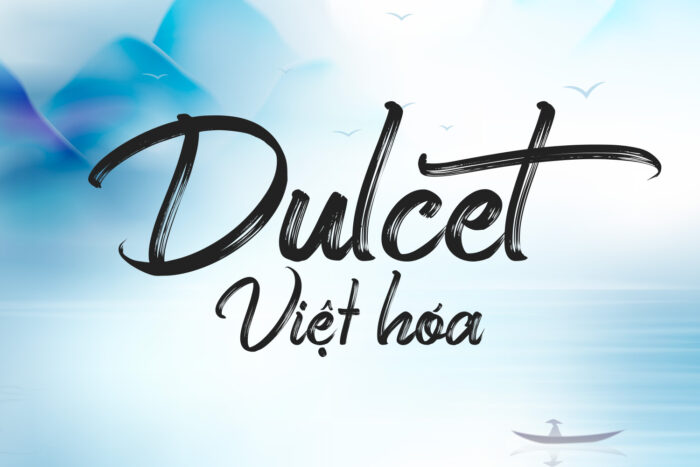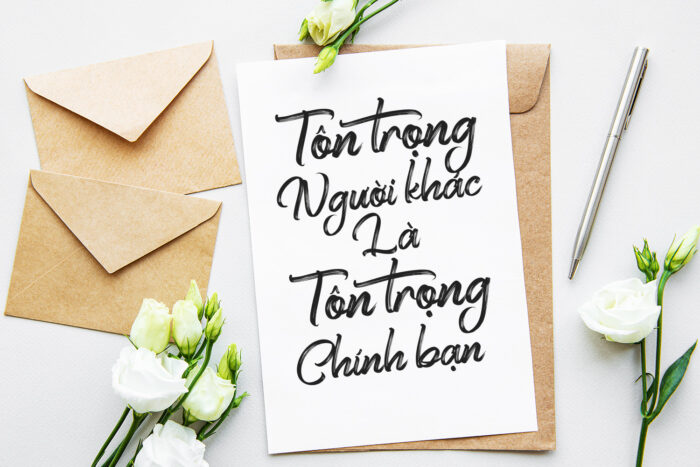
DVN Dulcet Script Việt hóa – Font chữ thư pháp tuyệt đẹp
“Dulcet Script” là một font chữ viết tay mang phong cách thư pháp, thể hiện sự uyển chuyển và mềm mại trong từng nét chữ. Với các đường nét uốn lượn tinh tế và độ dày mỏng vừa phải, font chữ này mang lại cảm giác êm dịu và trang nhã, phù hợp cho các thiết kế đòi hỏi tính thẩm mỹ cao. Các ký tự được thiết kế với sự cân đối và hài hòa, giúp dễ đọc và tạo ấn tượng mạnh về mặt thị giác.
“Dulcet Script” là lựa chọn lý tưởng cho các dự án sáng tạo như thiệp mời, bao bì sản phẩm, logo, và tiêu đề trang web, nơi mà phong cách viết tay mang lại sự gần gũi và tính cá nhân hóa. Font chữ này cũng phù hợp cho các dự án liên quan đến lĩnh vực thời trang, làm đẹp, hoặc nội thất, giúp tạo ra sự sang trọng và cuốn hút, góp phần nâng cao giá trị thẩm mỹ cho sản phẩm hoặc thương hiệu.v